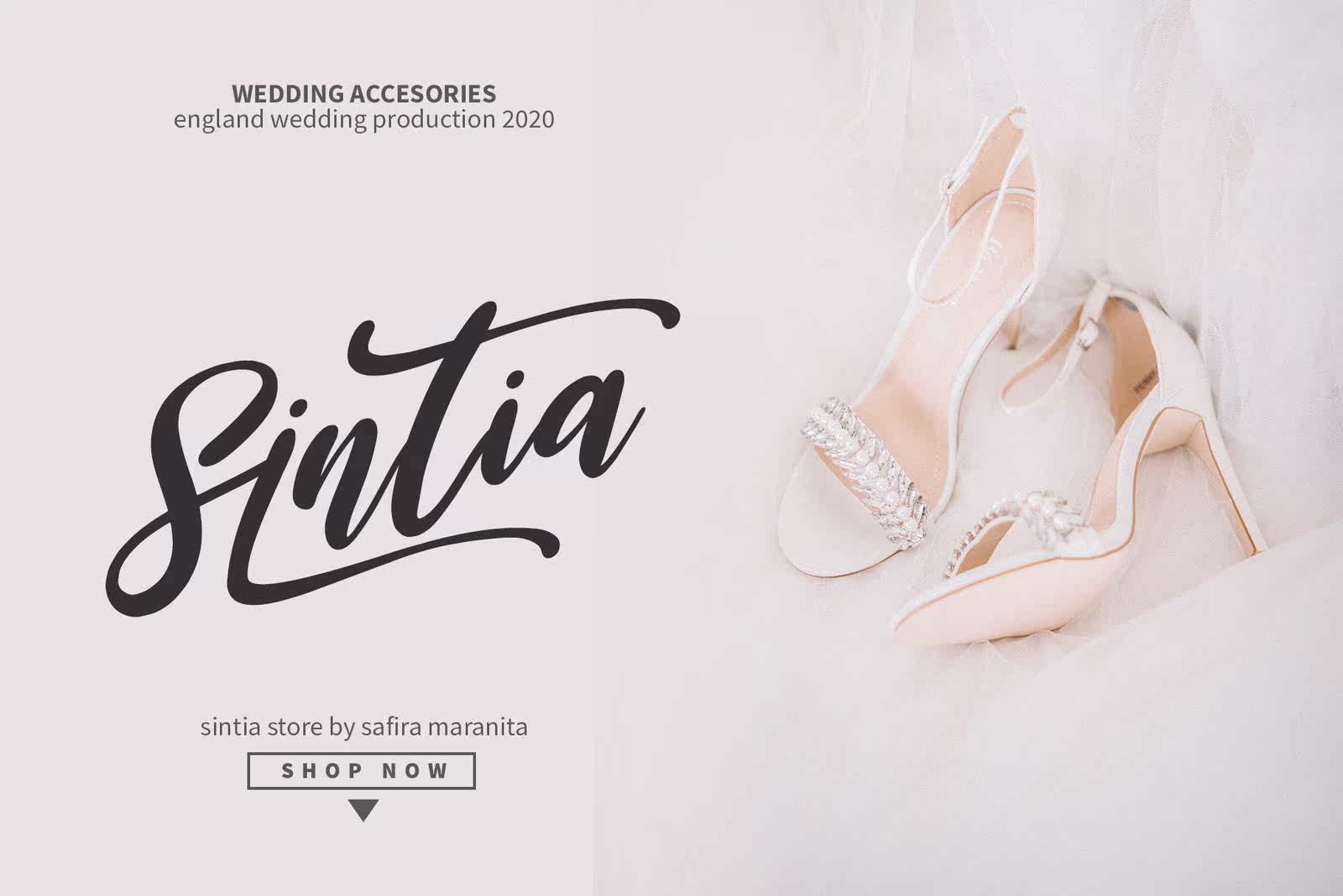
AMSTERDAM脚本字体。适合您的项目的文字和数字集合非常适合于标识、品牌设计、标识设计、数字刻字艺术、T恤/服装、海报、杂志、标志、广告设计和任何设计需求。AMSTERDAM脚本字体。适合您的项目的文字和数字集合非常适合于标识、品牌设计、标识设计,数字文字艺术、T恤/服装、海报、杂志、标志、广告设计和任何设计需求。